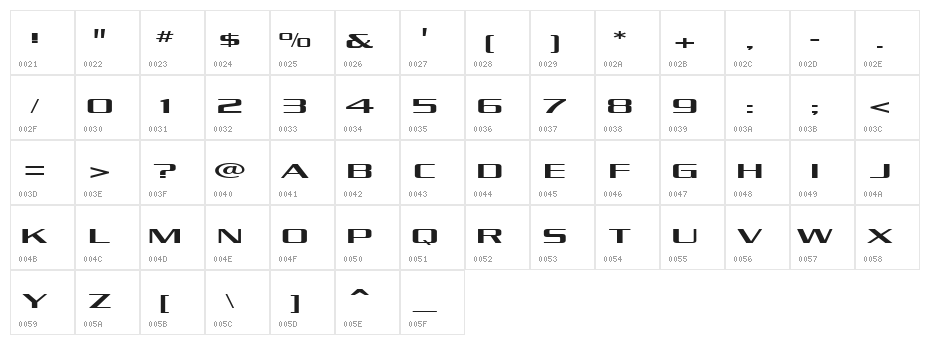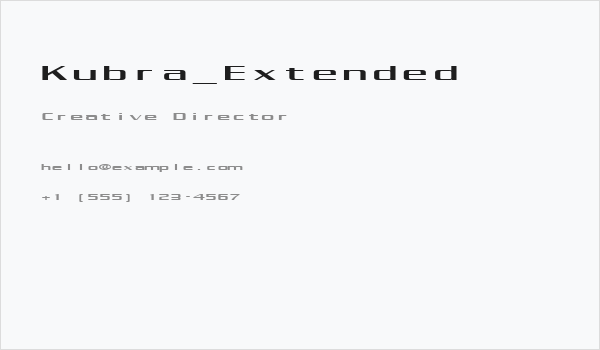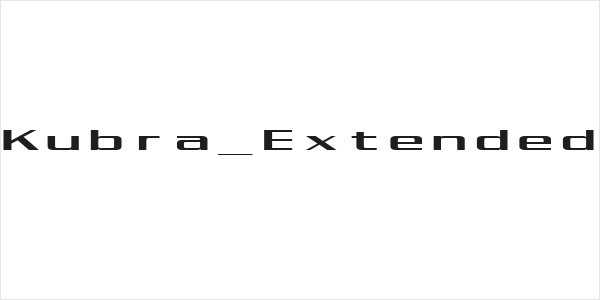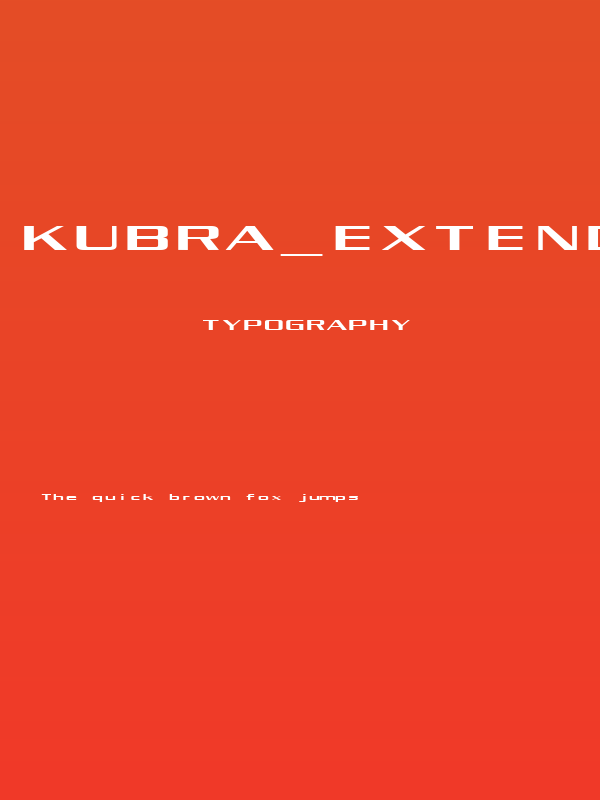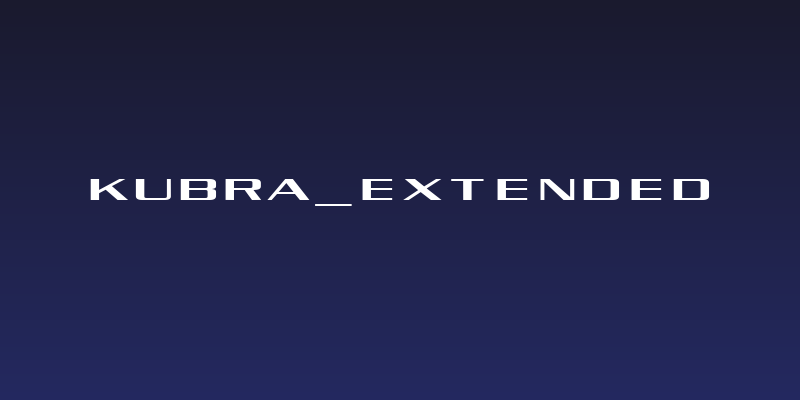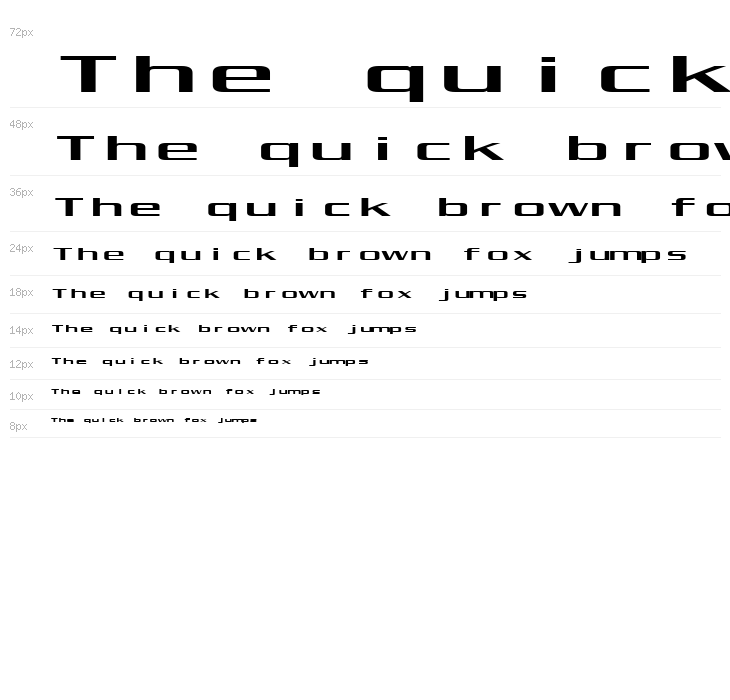
Kubra_Extended Font
| Kategorien | Formal |
| Breite | Expanded |
| Anwendungsfall | Headlines, Logos, Digital Interfaces |
| Vorgeschlagene Projekte | Ideal for technology branding, digital interfaces, video game design, and futuristic-themed projects. |